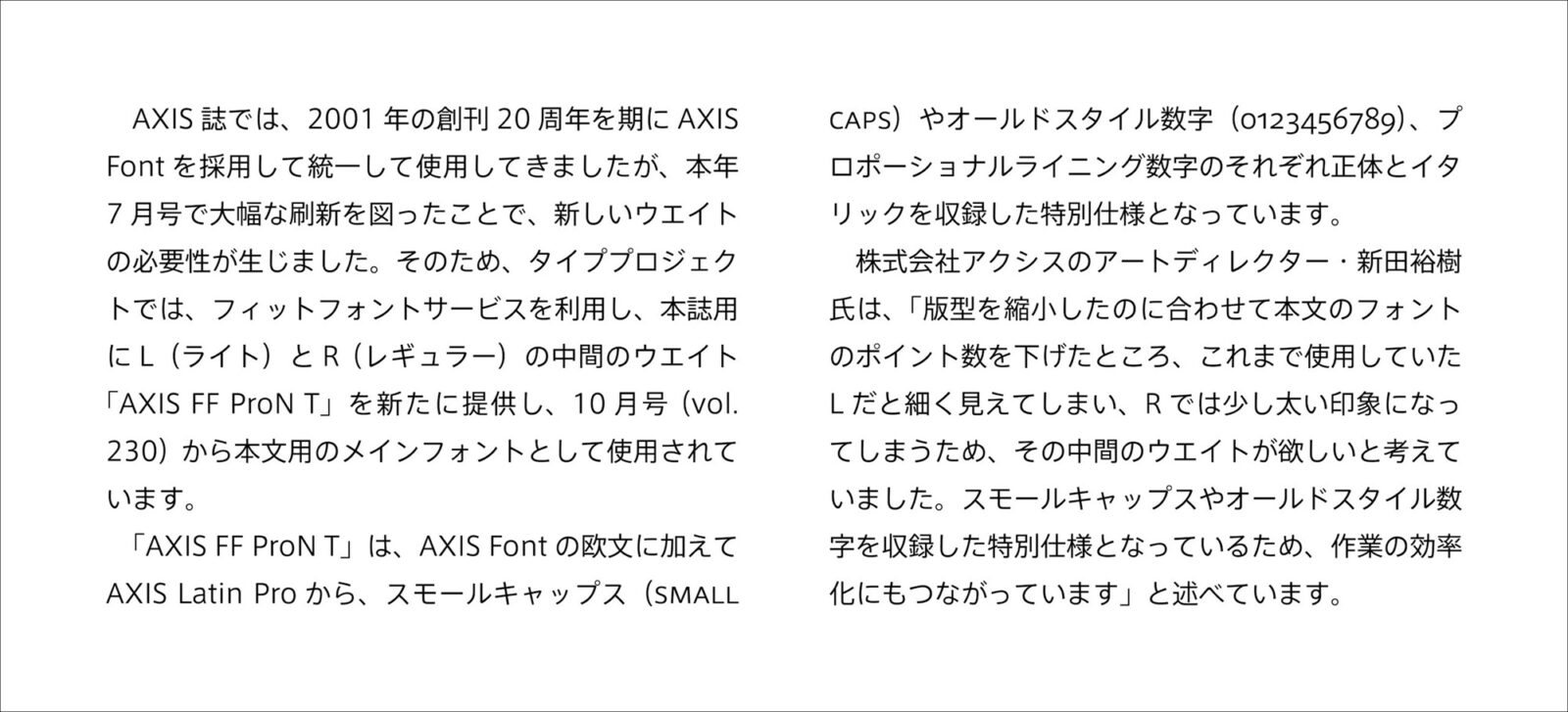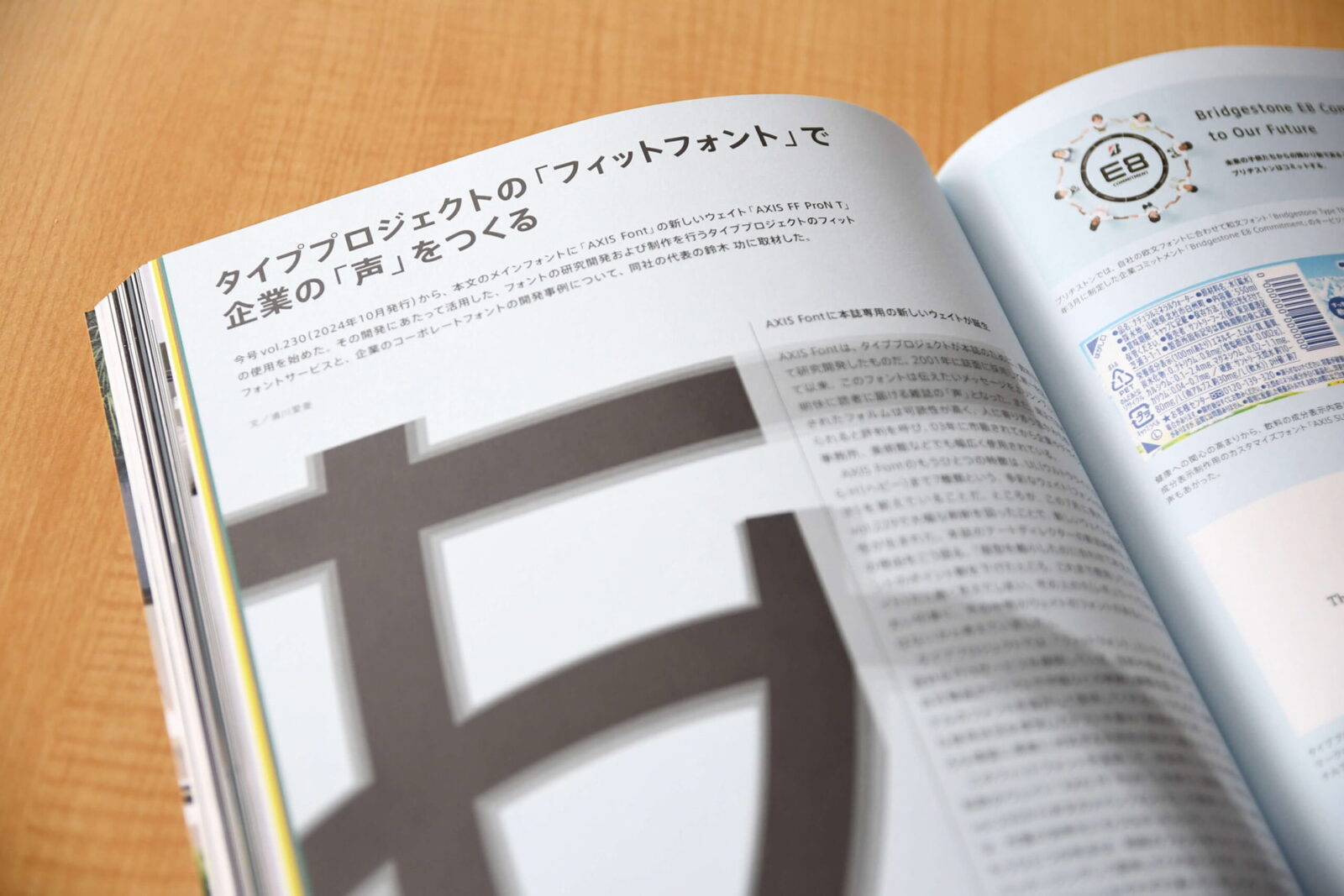
タイププロジェクト、AXIS誌専用フォントを提供
フィットフォントで本文用のメインフォントを調整
タイププロジェクト株式会社(東京都練馬区 代表取締役社長 鈴木 功)は、本日、株式会社アクシスが発行するAXIS誌専用フォントとして、AXISフィットフォントを調整した「AXIS FF ProN T」を提供したことを発表しました。
AXIS誌では、2001年の創刊20周年を期にAXIS Fontを採用して統一して使用してきましたが、本年7月号で大幅な刷新を図ったことで、新しいウエイトの必要性が生じました。そのため、タイププロジェクトでは、フィットフォントサービスを利用し、本誌用にL(ライト)とR (レギュラー)の中間のウエイト「AXIS FF ProN T」を新たに提供し、10月号 (vol.230) から本文のメインフォントとして使用されています。
「AXIS FF ProN T」は、AXIS Fontの欧文に加えて、AXIS Latin Proのスモールキャップスやオールドスタイル数字、プロポーショナルライニング数字のそれぞれ正体とイタリックを収録した特別仕様となっています。
株式会社アクシスのアートディレクター 新田 裕樹氏は、「版型を縮小したのに合わせて本文のフォントのポイント数を下げたところ、これまで使用していたLだと細く見えてしまい、Rでは少し太い印象になってしまうため、その中間のウエイトが欲しいと考えていました。「AXIS FF ProN T」誌面のサイズやフォントのポイント数とウエイトのバランス、視認性や可読性などのテストを重ねました。スモールキャップスやオールドスタイル数字を収録した特別仕様となっているため、作業の効率化にもつながっています」と述べています。
タイププロジェクトの代表取締役 鈴木 功は、「AXIS誌とともに歩んできたAXIS Fontを、雑誌の判型変更をともなう今回のリニューアルに際して、誌面に最適なフィットフォントとして新たに提供できたことを嬉しく思います」と述べています。
タイププロジェクトでは、企業のメッセージを伝えるための手段としてフォントによるブランディングを提案しています。フィットフォント技術を用いて、AXIS FontやTP明朝、TPスカイのウエイトや字幅、コントラスト、フトコロ軸を調節することで最適な組合せを提供します。欧文部を他社欧文と組替えるほか、オリジナルのひらがなやカタカナを開発するなど、世界有数のグローバル企業にコーポレートフォントを提供しています。